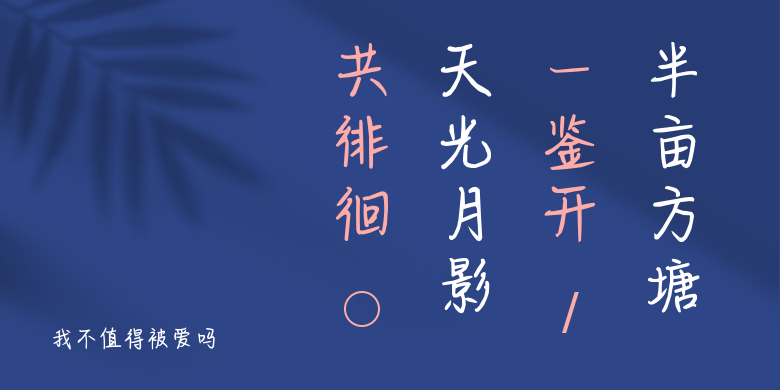
我不值得被爱吗
我不值得被爱吗,这款字体结构工整、笔画清晰,兼顾美观与易读性,适用于标题、正文、海报、包装、LOGO 等多种场景。字形优雅稳定,风格百搭耐看,适配日常排版与创意设计,让文字呈现更舒适、更具质感。我不值得被爱吗一笔一画,皆是细节,以均衡的比例、流畅的线条打造舒适视觉体验,字形端正大气,风格简约现代。无论是商业设计、品牌宣传还是日常排版,都能轻松驾驭,让文字更有格调与力量。我不值得被爱吗字体下载。